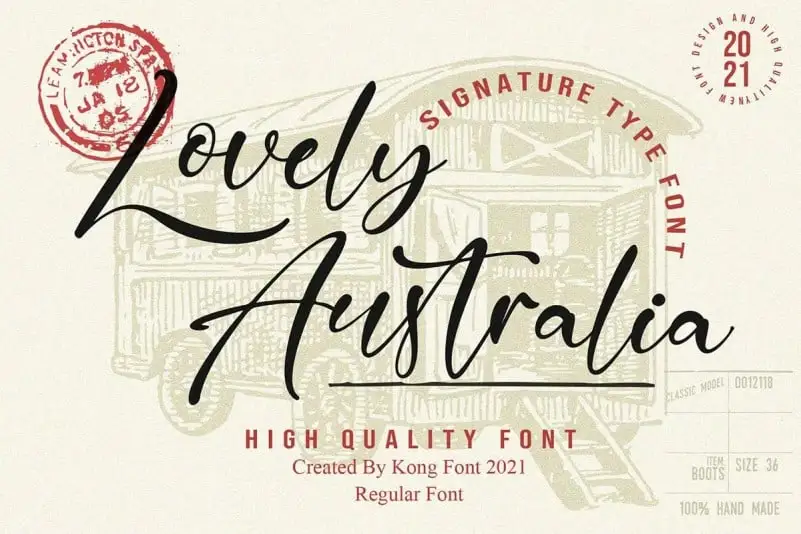
Lovely Australia Script Font – Download Grátis
A Lovely Australia Script Font é uma fonte elegante criada pelo designer Kong Font, projetada para apresentar uma sensação moderna e sofisticada. Esta fonte atinge perfeitamente os requisitos necessários para criar logotipos de assinatura e marcas de papelaria em uma sessão de fotos ou convites de casamento. É especialmente adequada para assinaturas iniciais ou identidades de marca, oferecendo uma opção versátil que pode ser usada tanto nos detalhes quanto nas cores da sua marca. Esta fonte é perfeita para quem busca um toque sofisticado e moderno em seus materiais gráficos.